【案例研究】字體即戰略:台灣企業如何為品牌選擇專屬字體
導讀:在全球化與數位化的品牌經營中,視覺一致性是建立品牌信賴感的關鍵。對於跨國企業或注重質感的品牌而言,如何在官網、App、行銷文宣等多元應用場景中,快速找到一套既能傳遞品牌精神,又完美支援多語言的字體,是一大挑戰。
在 Monotype Fonts 的專業字體平台上,企業能系統化地完成字體策略,為不同「使用情境」精準挑選具備多語言支援與豐富風格的字體。以下透過六大台灣品牌案例,具體說明如何從「品牌需求」出發,並在平台上找到相對應的「解決方案與應用」,讓字體成為貫穿所有消費者接觸點的戰略核心。
1|華碩電腦(ASUS)
品牌需求:作為全球知名的科技品牌,需要為不同產品線、地區市場和應用場景建立統一而又靈活的視覺系統,確保在全球各市場的視覺一致性與品牌識別度。
平台應用:透過 Monotype Fonts 平台,華碩建立了一個包含 30+ 字體的完整字體庫,包括 Myriad、Square、Futura、M Hei、Helvetica Now 等。平台提供統一管理不同地區網站的字體授權,確保多語言顯示一致性,並針對不同產品線配置專屬字體組合,靈活應用於各種行銷場景。
2|宏達國際電子 (HTC)
品牌需求:在 Web 與 App 的使用者介面 (UI) 中,需要冷靜、客觀且極具可讀性的字體。
平台應用:HTC 選用的 Gotham 在 Monotype Fonts 平台上是一個龐大的字體家族。設計團隊可以輕鬆地在平台上預覽 Gotham Book, Gotham Medium, Gotham Bold 等不同字重在介面上的表現,並確認其對歐洲語言(如英文、法文、德文)的支援度。這讓他們能一套字體走天下,用於標題、內文、按鈕等各種 UI 元素,確保全球使用者體驗的清晰與統一。
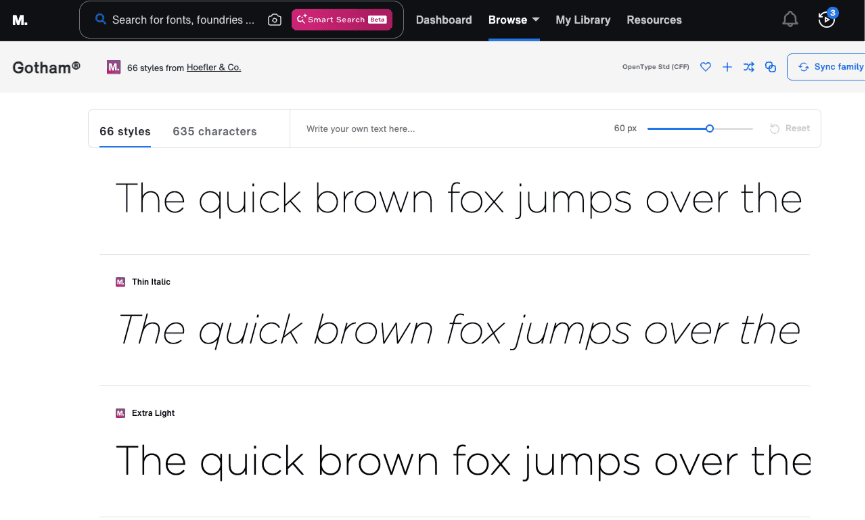
3|凱基證券 (KGI Securities)
品牌需求:在數位與實體廣告等多元媒體上,建立「穩健中求創新」的專業金融形象。
平台應用:凱基證券使用的 蒙納盈富體 M Finance HK,是蒙納特別為專業服務行業,如金融業,開發的專業字體。在平台上,企業不僅能獲取這款專為繁體中文優化的字體,更能找到與其風格匹配的英文無襯線體,形成一套完整的品牌字體組合。這確保了凱基證券在 OOH 大型看板、手機廣告等任何接觸點上,,字體視覺都能傳遞出無可挑剔的專業感與穩固的信任感。
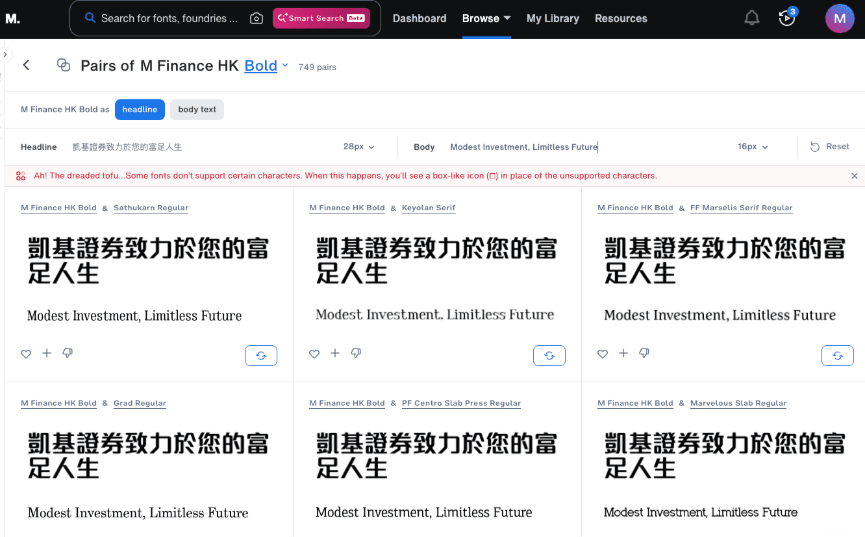
4|台灣大哥大(Taiwan Mobile)
品牌需求:在電信服務的激烈競爭中,建立親切、可靠且具質感的品牌形象,同時在各種客戶接觸點維持一致的視覺體驗。
平台應用:選用 M Elle HK Medium 作為主要品牌字體,透過 Monotype Fonts 平台統一門市招牌、宣傳文宣、數位平台的視覺呈現,確保在各種載體上都能保持優雅、親切的品牌調性。
5|永聯物流開發(Ally Logistic Property)
品牌需求:在官方網站上清晰呈現複雜的物流園區資訊,同時傳遞智能、高效與前瞻的企業形象。
平台應用:永聯物流開發選用的 Avenir Next,是 Monotype Fonts 平台上備受推崇的幾何無襯線字體家族。其最大的優勢在於擁有極寬廣的字重與寬度選擇,並對多國語言字元提供良好支援。網頁設計師可以透過平台,靈活調配 Avenir Next 的 Light、Regular、Heavy 等字重,用於數據呈現、標題層級與內文說明,在複雜資訊中建立清晰的視覺秩序,展現國際化企業的專業度。
6|台灣傑太日煙國際 (JT Tobacco International Taiwan Corp)
品牌需求:在嚴格的行銷規範下,繞過直接的產品宣傳,為品牌塑造一種「低調奢華」與「精緻生活風格」的國際品牌形象。
平台應用:在 Monotype Fonts 平台中,傑太日煙可以蒙納雅麗體(M Elle HK)為基礎,尋找其英文對應的優雅襯線體(如:FF Marselis Serif,見下圖)。 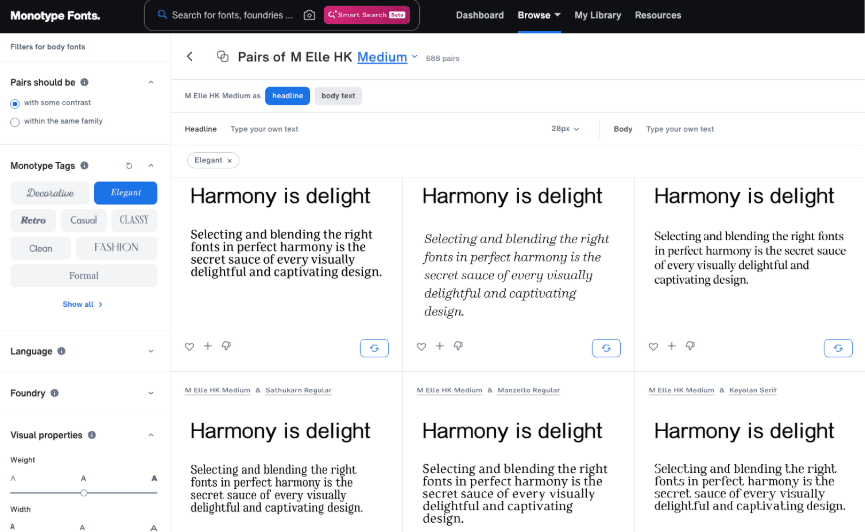
7|立新寢具 (LY Shin Bedding Co., Ltd.)
品牌需求:在品牌識別與平面廣告中,建立浪漫、舒適且高質感的視覺印象。
平台應用:立新寢具使用的 Monotype Corisva,其本身就是蒙納旗下的經典字體。在平台上,他們可以探索這款字體的其他字重(如細體、粗體)或斜體,應用於不同的文宣層級。同時,平台能提供與 Corisva 氣質相近的英文襯線體作為搭配建議,確保品牌在需要中英混排的視覺設計中,依然能完美傳遞其「溫柔呵護」的承諾。
結語:
透過 Monotype Fonts 專業字體平台的視角,我們可以看到,現代企業的字體選擇已不再是單點尋找一款好看的字。而是一套系統化的策略:在平台上,根據「使用情境」(UI、品牌識別、官網、廣告),篩選出兼具「多語言支援」與「豐富字體家族」的解決方案。這讓品牌視覺能夠智慧地適應各種應用場景,無論溝通媒介如何變化,都能向消費者傳遞一致而強有力的品牌聲音。